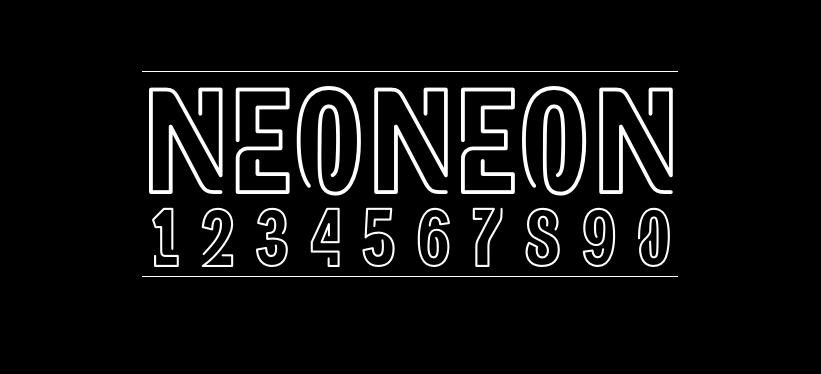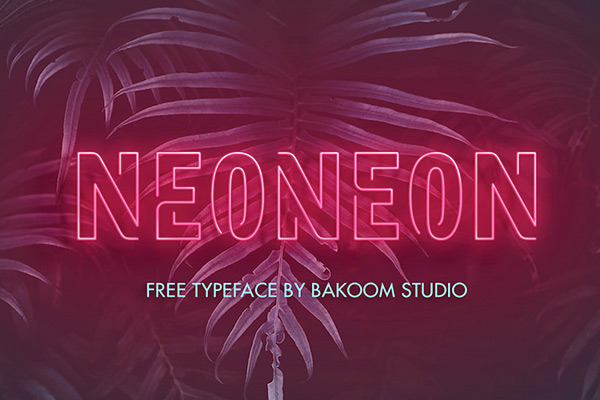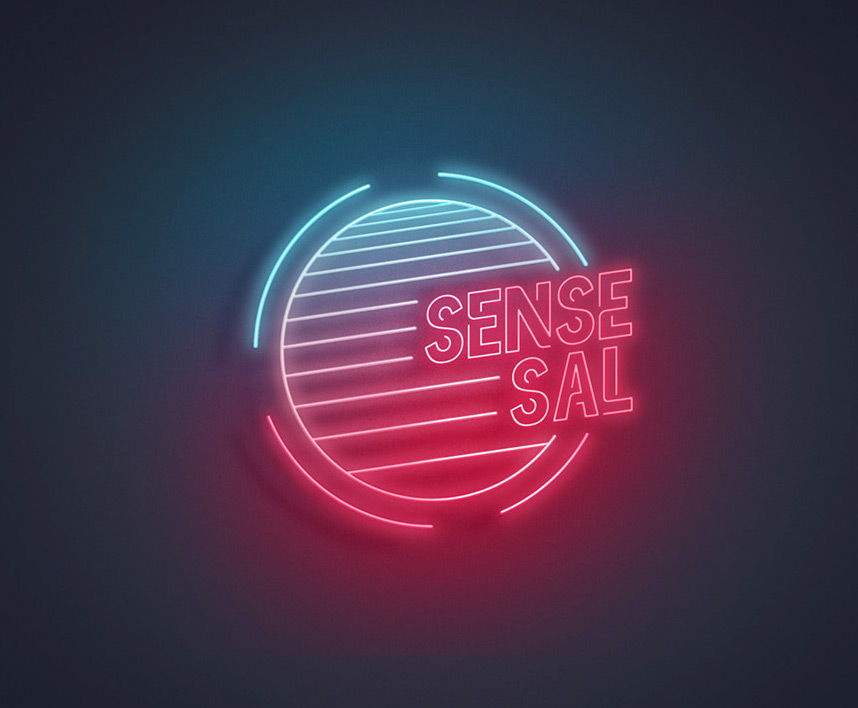
NEONEON
NEONEON字体介绍
Noeoneon是一种霓虹灯风格的字体,在Photoshop中特别发光时效果最好。它是一种多用途的字体,模仿80年代的标牌样式。可用于广告,包装,海报设计等。
Noeoneon是Bakoom Studio设计的第一个字体,一家来自西班牙的设计咨询公司。
NEONEON字体应用示例